30 необычных бесплатных кириллических шрифтов
Сегодня мы решили собрать для вас в одном месте необычные кириллические шрифты, которые могут вам пригодиться. А, возможно, просто пополнят вашу коллекцию и будут у вас лежать “на всякий случай”. В общем, смотрите, скачивайте, наслаждайтесь. Главное, что все они бесплатны.
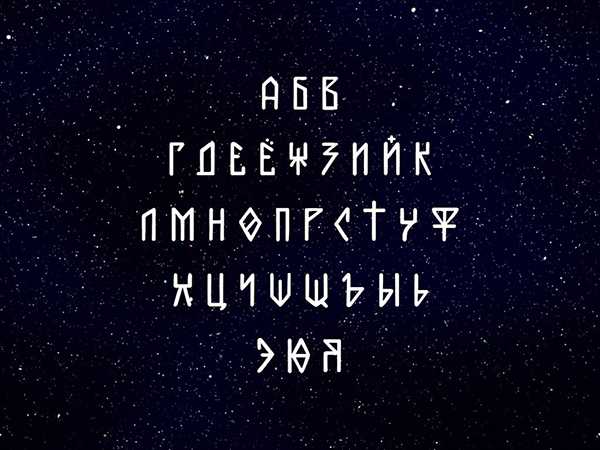
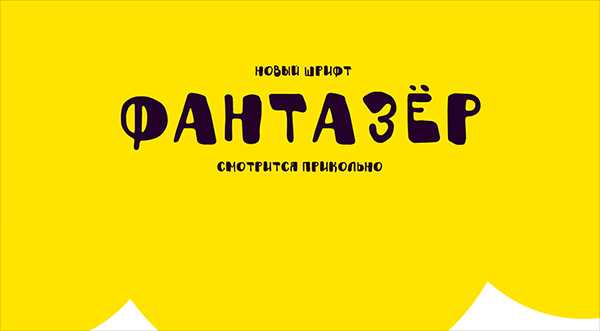
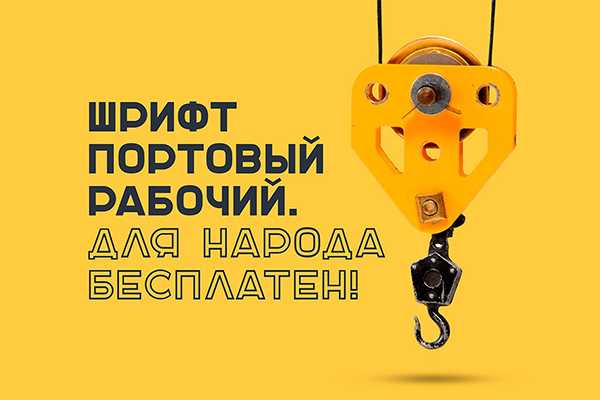
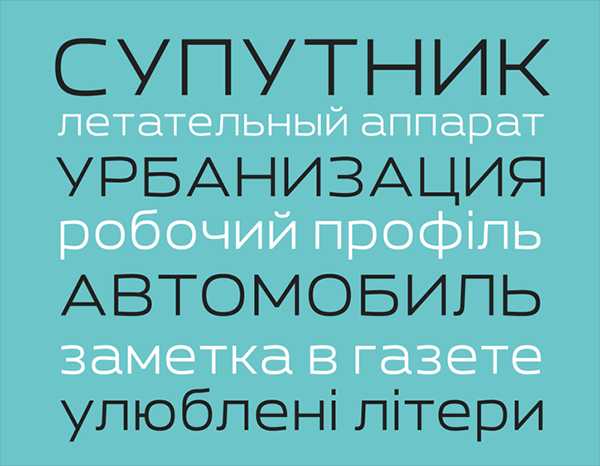
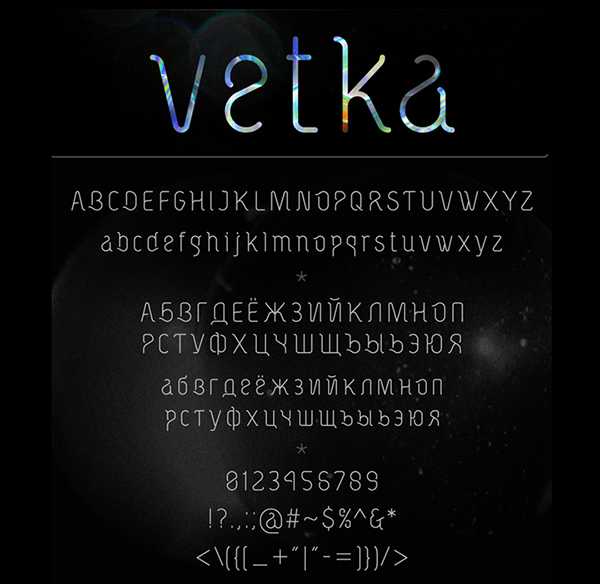
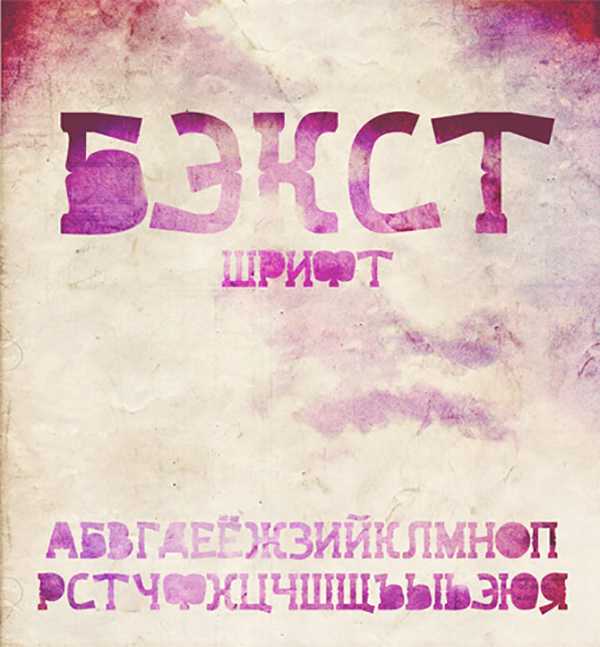
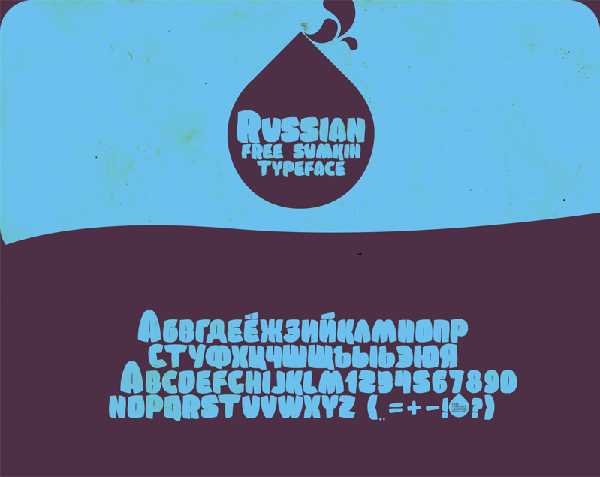
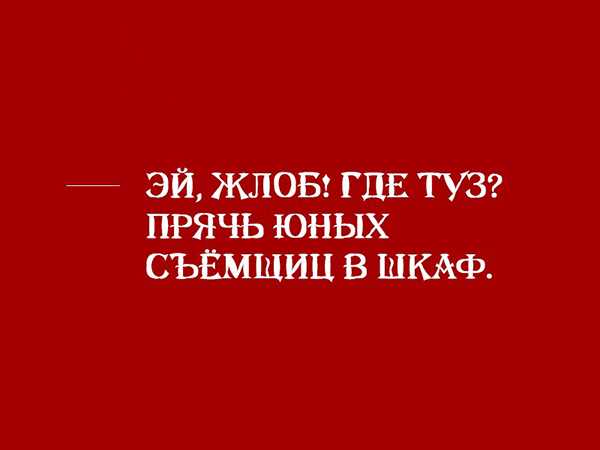
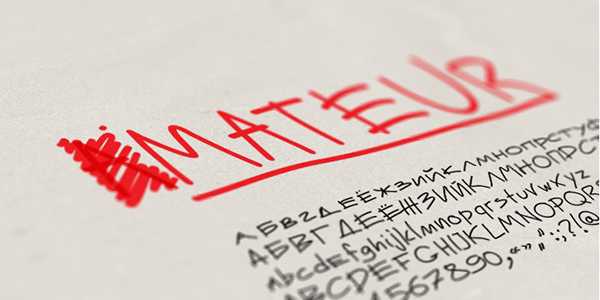
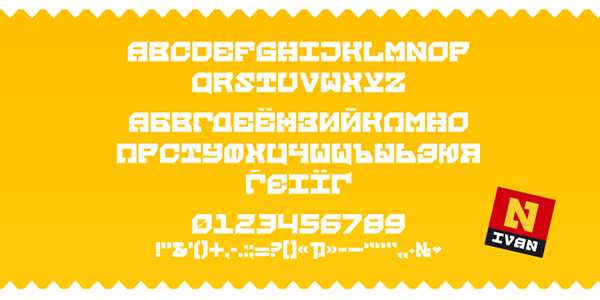
Лучшие кириллические шрифты 2017
За последние годы в арсенале дизайнеров появились сотни превосходных, новых кириллических шрифтов. Мы отобрали десять самых используемых и привлекательных русских шрифтов за последнее время.
Какой шрифт лучше? Какие шрифты лучше использовать? Это зависит от задачи, которую вам предстоит решить.
1. Arkhip
2. Boucle
3. Cabana
4. Eirik Raude
5. Gogoia
6. Muller
7. Nexa Script
8. Nickainley
9. Dewberry
10. Pobeda
Не стоит обходить вниманием и платные шрифты. Как правило, они более тщательно проработаны чем их бесплатные аналоги, и содержат более широкий набор символов.
11. Tesla
11. Tilda
К сожалению, качественных кириллических шрифтов не так много как хотелось бы. Но отслеживается, безусловно, позитивная тенденция к росту их количества. Всё больше отечественных дизайнеров трудятся над русификацией западных популярных шрифтов, а также дают жизнь своим, не менее качественным продуктам.
Что касается использования. Универсальных шрифтов для решения любых задач не существует. Шрифт, который прекрасно смотрится на бумаге – может выглядеть ужасно в качестве основной гарнитуры на веб-сайте. Именно поэтому разнообразие шрифтов сегодня так велико, и у каждого из них своё предназначение. Например, акцидентный шрифт не стоит использовать для набора сплошного и мелкого текста, также как не стоит использовать рубленые шрифты на веб-сайтах. В обоих случаях восприятие и читабельность текста будут сильно нарушены. Например, лучший шрифт для текста на сайте – Open Sans. Читабельный и привычный глазу шрифт для работы с документами – Times New Roman.
Начинающие дизайнеры часто задаются вопросом, «какие лучшие шрифты для логотипов». Ответ прост: читабельные. Если вы занимаетесь разработкой фирменного логотипа – не пытайтесь придать написанию какое-то конкретное художественное решение или стилистику. Например, не ищите шрифт с какими-нибудь шипами на буквах, если вы делаете логотип для цветочного магазина. Достаточно будет обратиться к ассоциациям (нежный, тонкий, изящный, в то же время достаточно контрастный, чтобы выдерживать масштабируемость).
В большинстве случаев, выбор шрифта для логотипа должен основываться на целесообразности использования той или иной гарнитуры в рамках единого композиционного решения. Например, если знак находится слева от шрифтовой части, и название достаточно длинное, скорее всего, подойдет узкий шрифт с небольшим кернингом. Если слово короткое, то напротив, можно сделать кернинг больше и шрифт выбрать более выразительный.
Вообще, нет каких-либо правил подбора шрифта. Его нужно чувствовать, и принимать адекватные решения. Например, если это медицинская тематика – вполне подойдут и антиква, и гротеск. Вряд ли подойдут рубленные. Если спортивная тематика – скорее всего динамический, наклонный шрифт, без каких либо засечек. Возможно разряженный.
Конечно, лучше всего сделать шрифтовое начертание логотипа уникальным. Это добавит логотипу оригинальности, а вам – авторитет в глазах своих коллег и своего клиента.
Подборка красивых русских шрифтов с изображениями в количестве 13 штук!, Не нужно гадать — как шрифт будет выглядеть на практике. Понравился — скачали!
1. Cony. Ве1сьма привлекательный шрифт. Скачать шрифт Cony
27. Bardo — классический элегантный ретро шрифт
28. Electronics — бесплатный жирный псевдо-рукописный шрифт
29. Shabrina — свежий и энергичный шрифт в стиле леттеринга
30. Sketch — бесплатный рукописный шрифт в стиле широкая кисть
31. Albondigas — каллиграфический шрифт для леттеринга и пр.
32. Messenger Pigeons — стильный бесплатный каллиграфический шрифт
33. Jumper — отличный маркерный «сухой» бесплатный шрифт